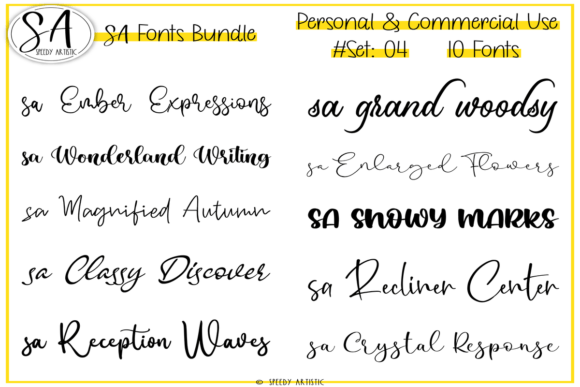
Script and Handwritten Bundle 4
Mencari elemen reka bentuk yang sesuai boleh menjadi mencabar, tetapi Script and Handwritten Bundle 4 menawarkan koleksi luar biasa yang menaik taraf karya anda serta-merta.
Sama ada anda mencipta produk POD (Print on Demand), jemputan perkahwinan atau grafik media sosial, Script and Handwritten Bundle 4 amat bersesuaian.